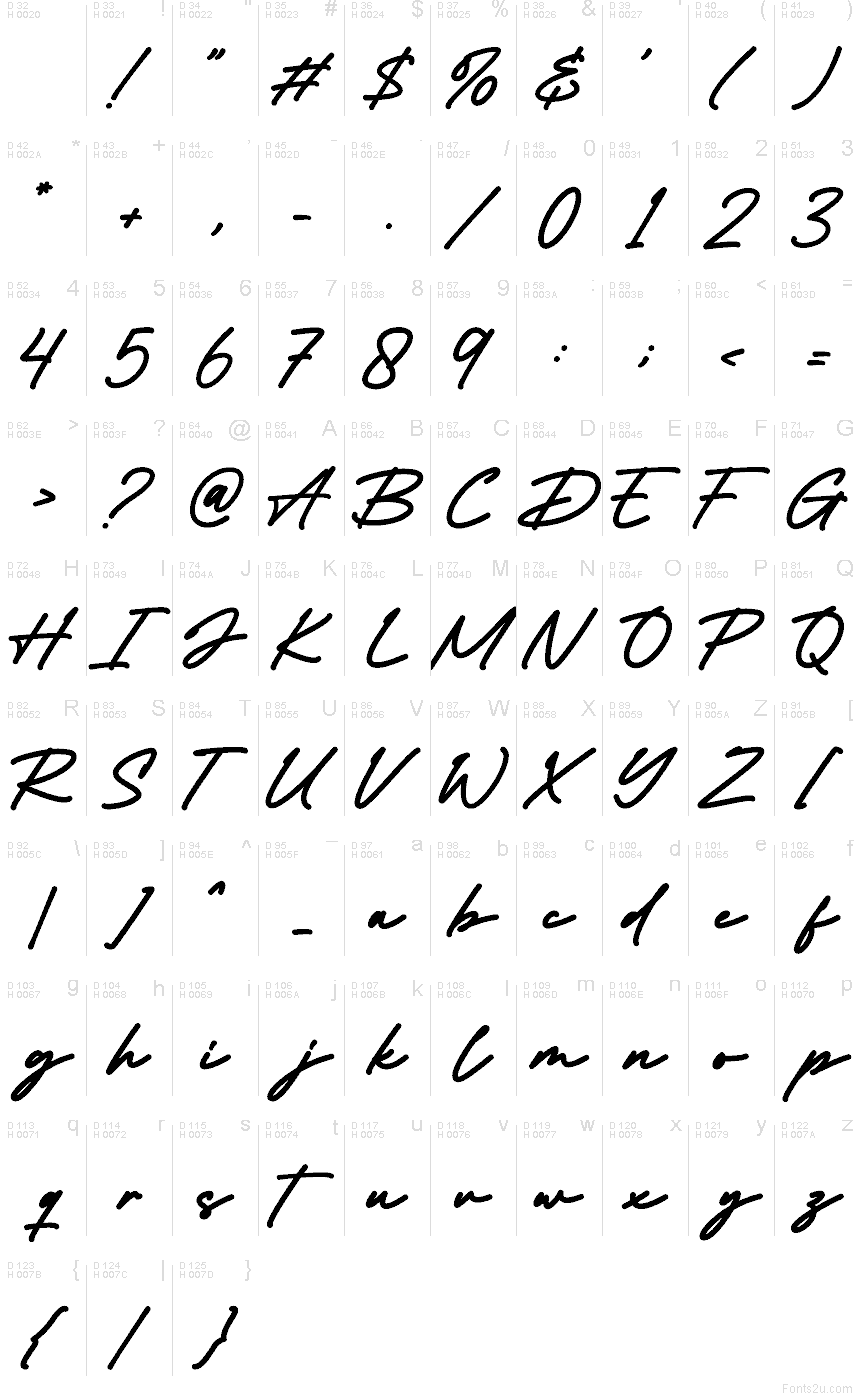
Huntley Signature od RantauType je bezplatné ručně psané písmo, které definují dlouhé křížící se tahy a rychlý, perem vedený rytmus. Písmena působí jako jeden sebevědomý pohyb přerušený ostrými změnami směru, což mu dodává uvolněnou autoritu osobního podpisu namísto učesané kaligrafie.
Tento pohyb skvěle vynikne v brandingu, butikovém balení, záhlavích sociálních sítí, pozvánkách nebo grafikách s citáty, kde rychlá ruční textura pomáhá ukotvit celý layout. Nejvíce z něj těží krátké názvy a titulky, protože rozšířené tahy a hranatá spojení dodají i pár slovům dostatečnou výraznost, aby orámovala vizitku, etiketu nebo obal bez potřeby dalších dekorací.